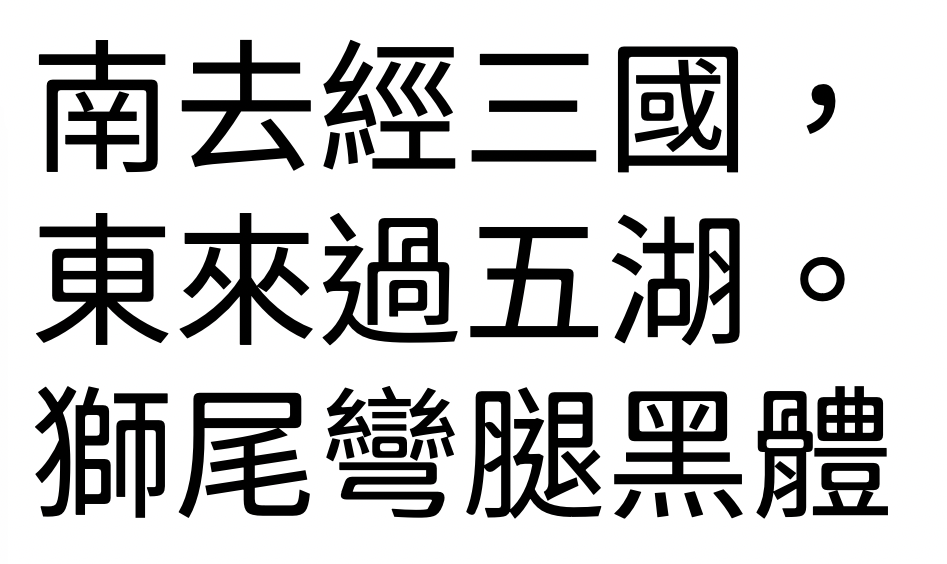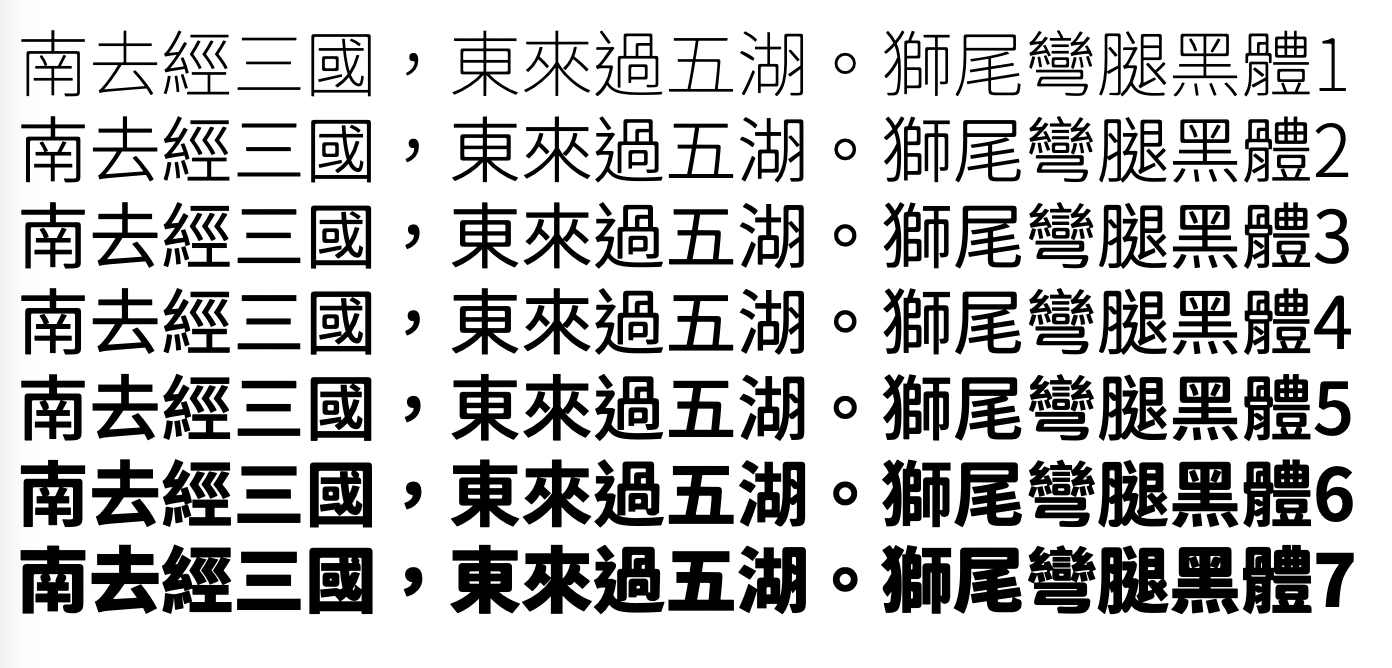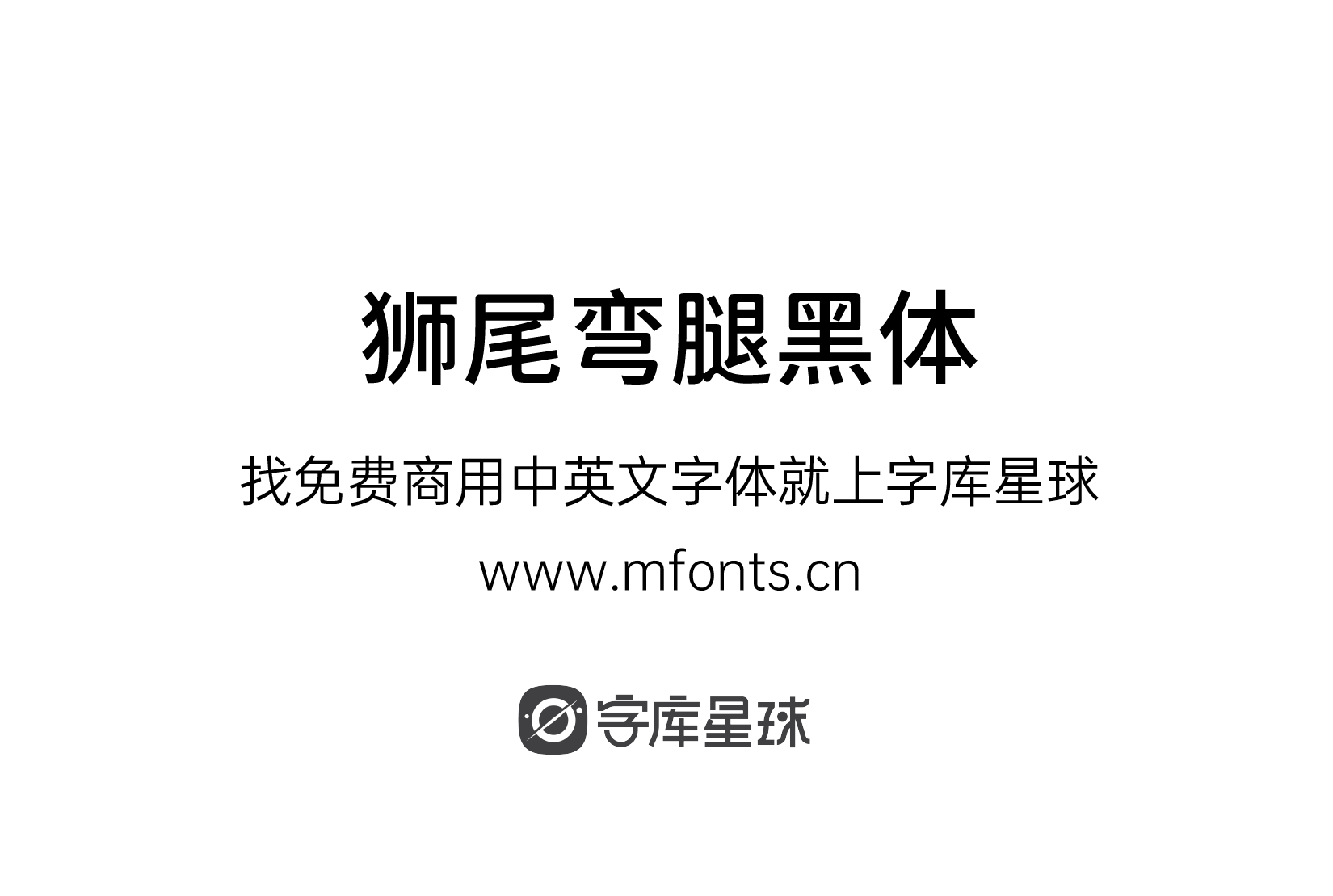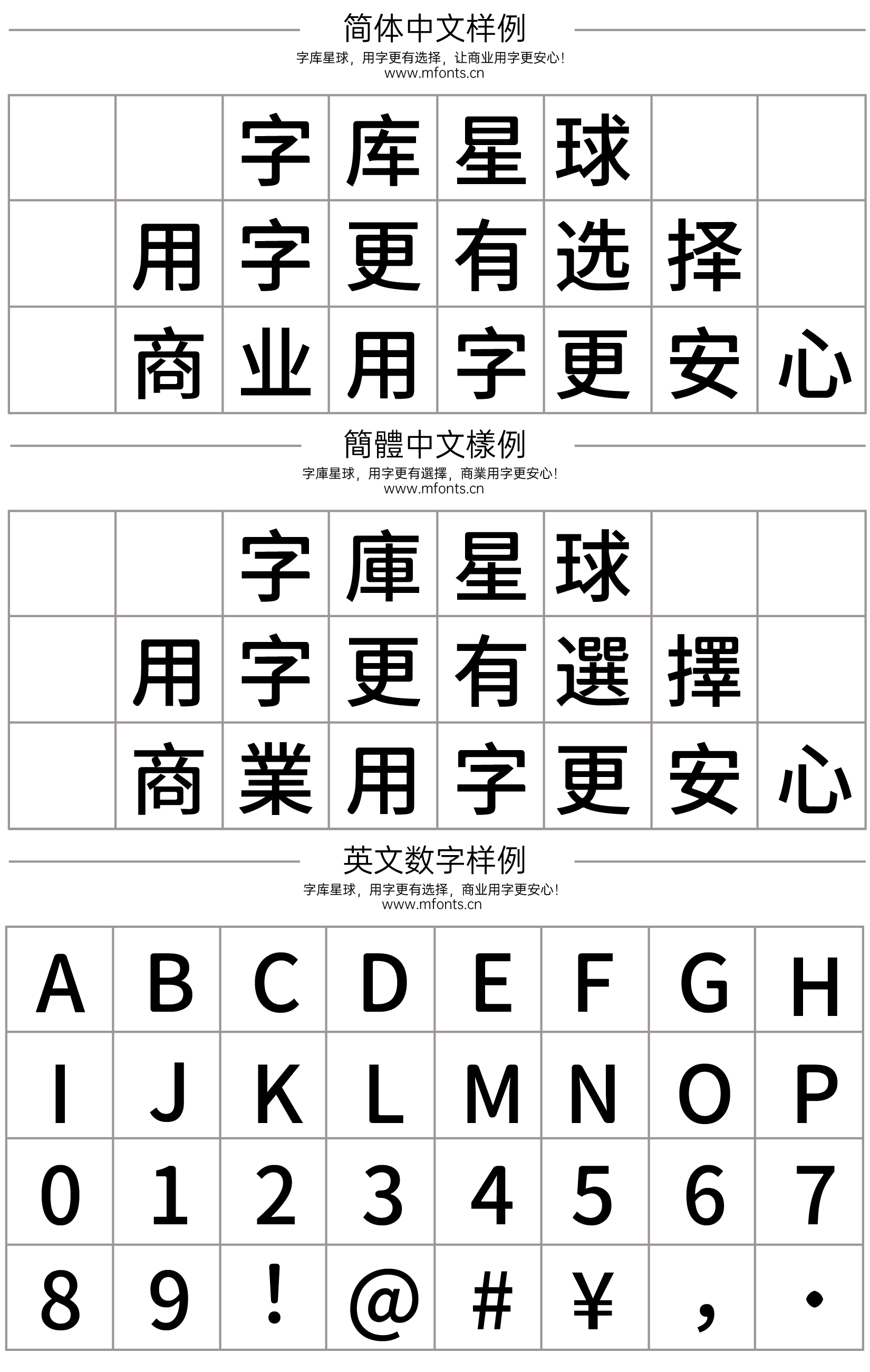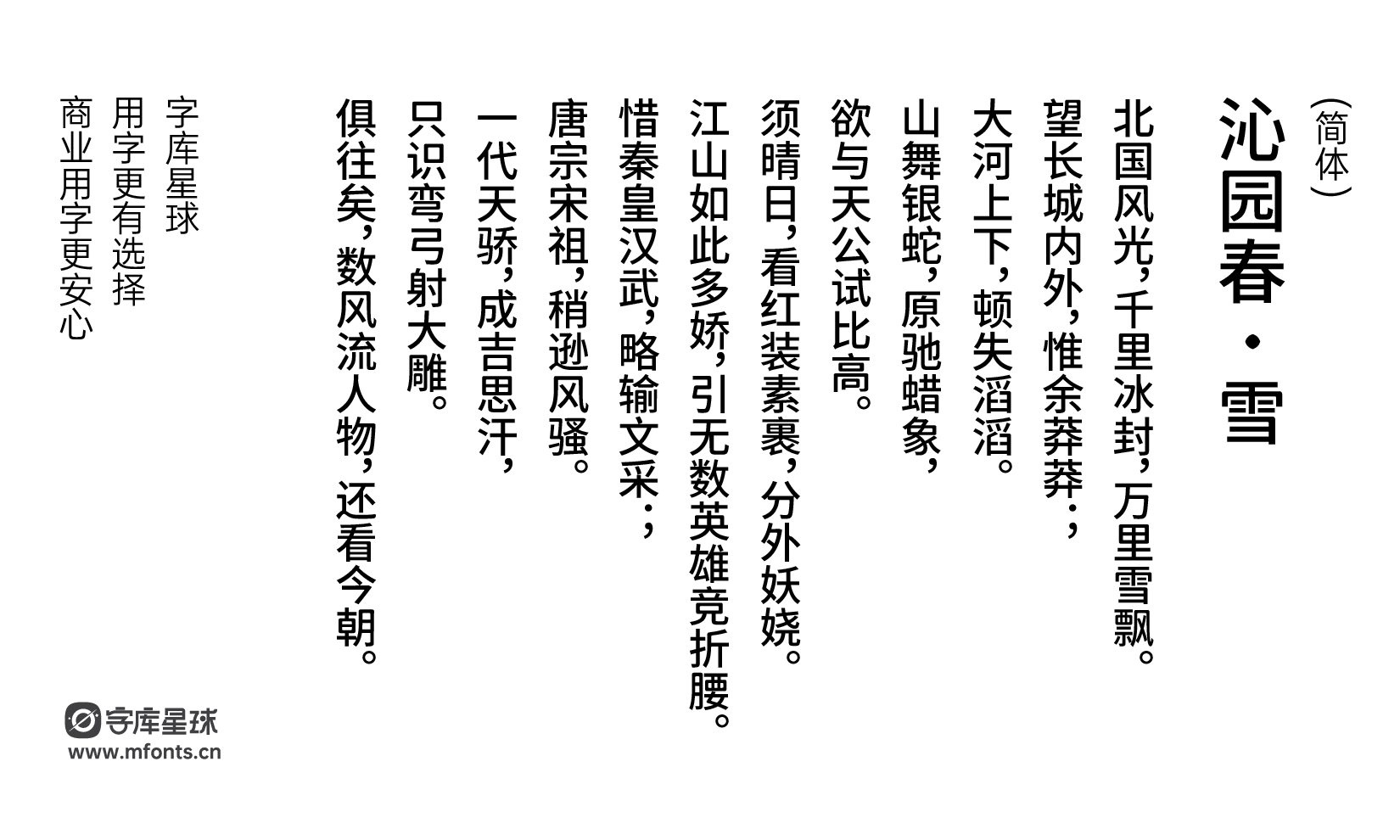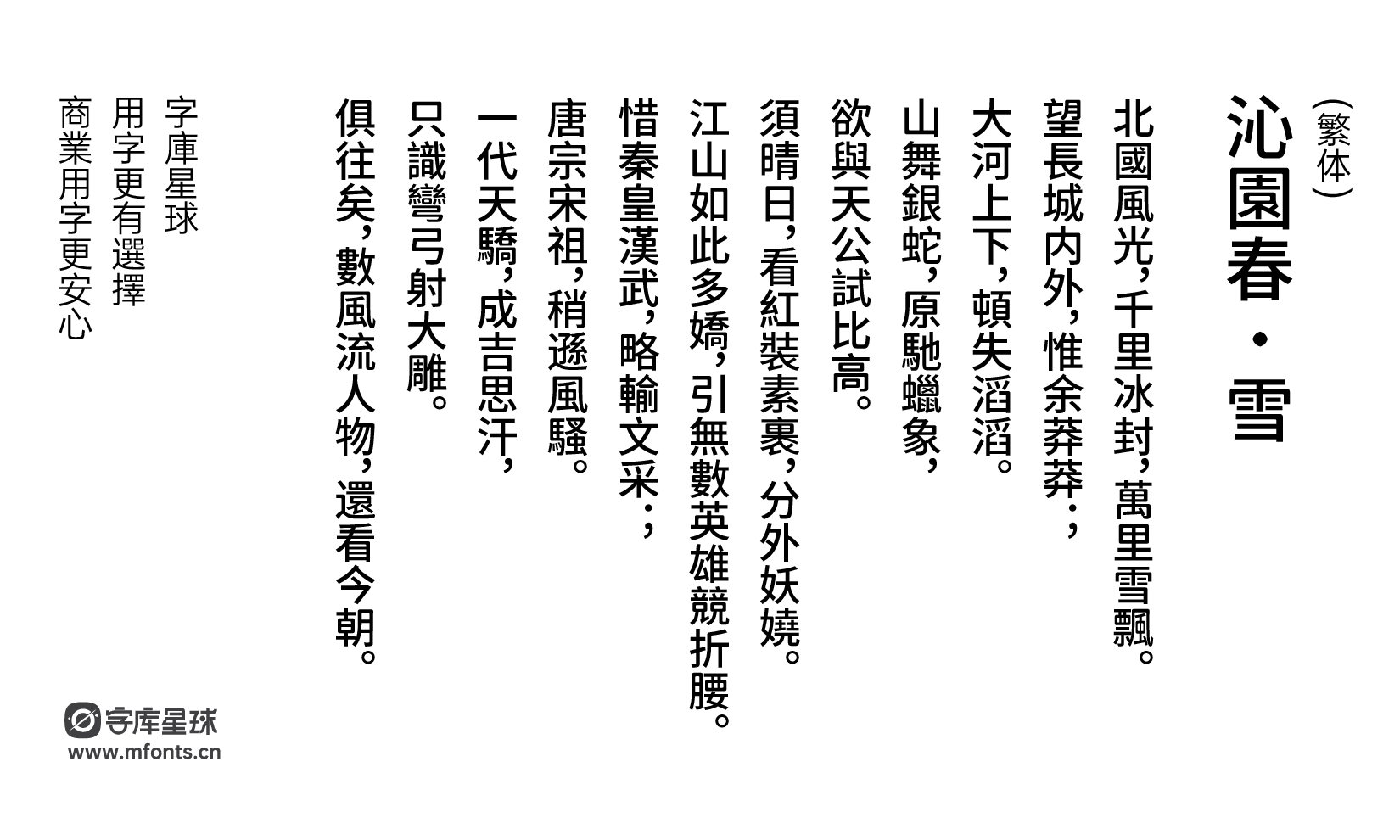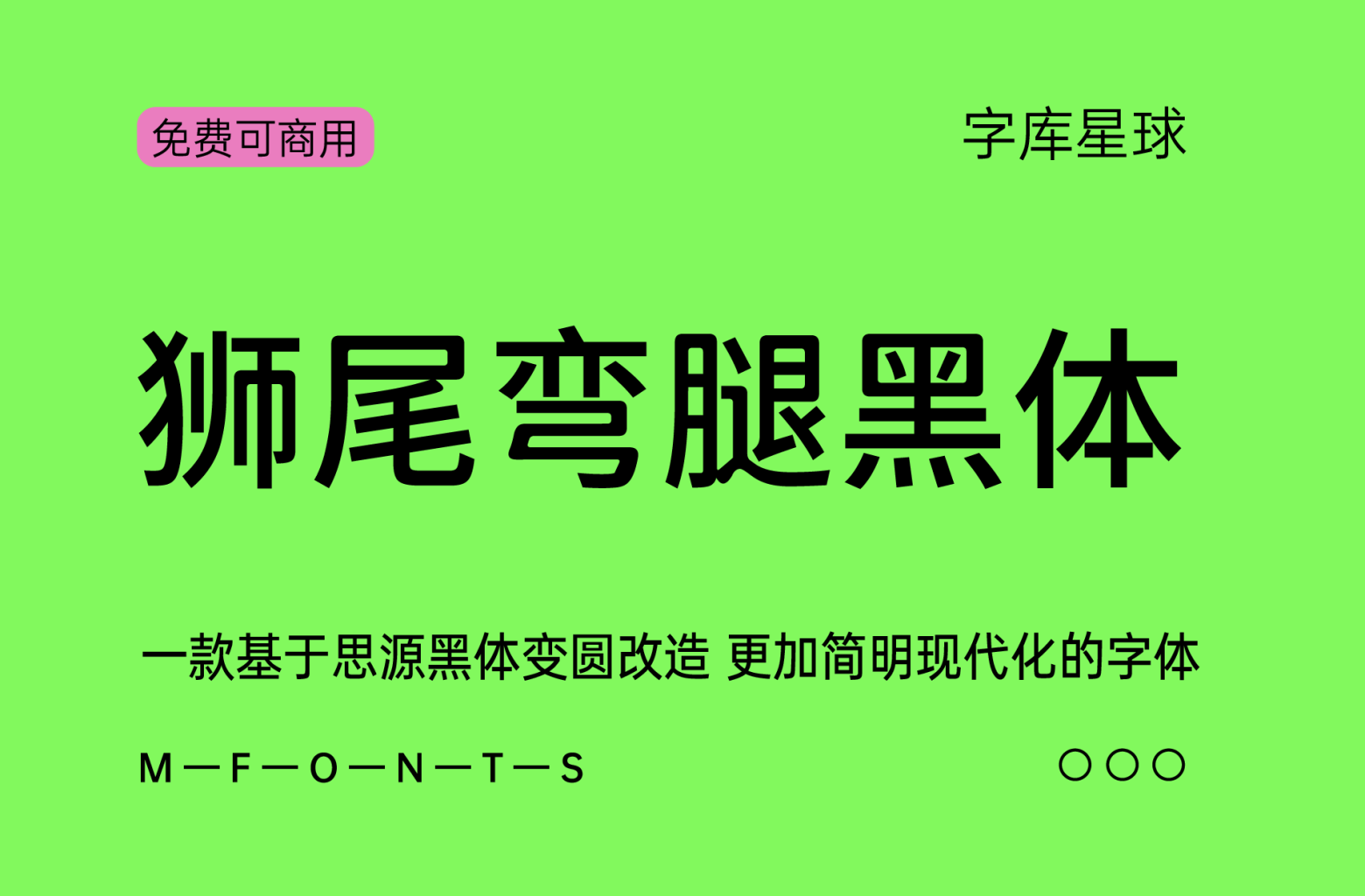
狮尾弯腿黑体
狮尾弯腿黑体基于思源黑体变圆改造,更加简明现代化的免费可商用字体。支援简体中文、繁体中文、韩文与日文;可以免费商用,欢迎大家自由应用、自由改作!
「狮尾弯腿黑体」与「狮尾腿圆体」差别在笔触是否有做调整,狮尾弯黑体所套用的效果较少,在笔触没有做调整。
「狮尾弯腿黑体」与「狮尾弯黑体」差别在有没有拔脚,「拔脚」就是会有较少的笔画,例如移除「口」字的左右下角会多出的短线条。有拔脚的字会较圆,但是会造成有些字因直接去掉腿后左右不平衡、左右不对衬的「悬空」问题。改使用「腿」系列字体就不会有这个问题。
和思源黑体一样,支持7种的字重:
字体后面的 SC,JP,TC是什意思?
• SC是 Simplified Chinese 简体中文,代表大陆习惯字形。
• TC是 Traditional Chinese 繁体中文,代表港台习惯的字形。
• JP是 Japanese 日文,代表日本习惯字形。
• 相同一个字,在不地区的书写方式可能会略有不同。